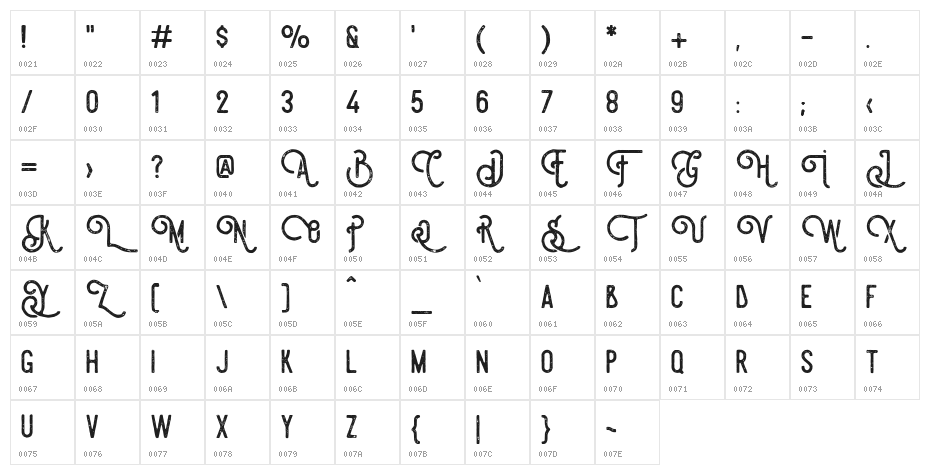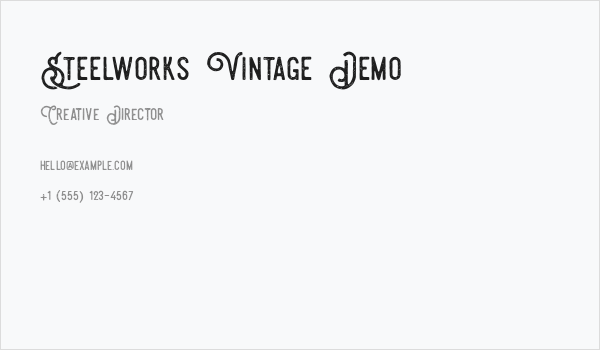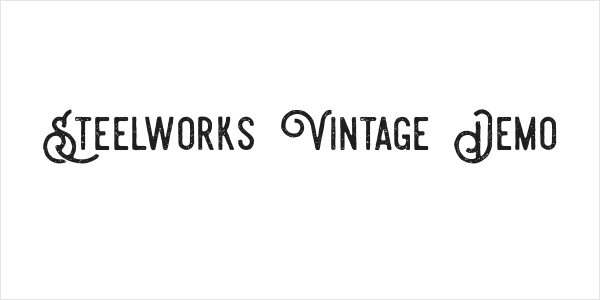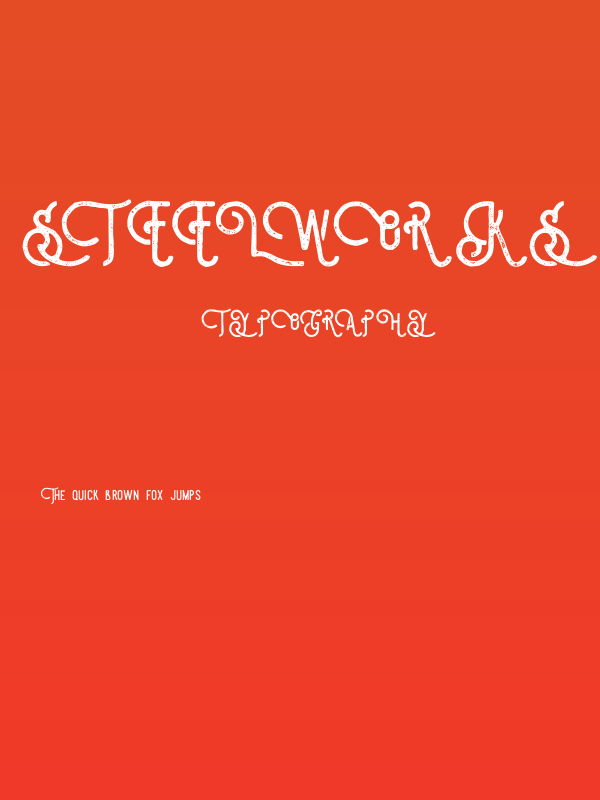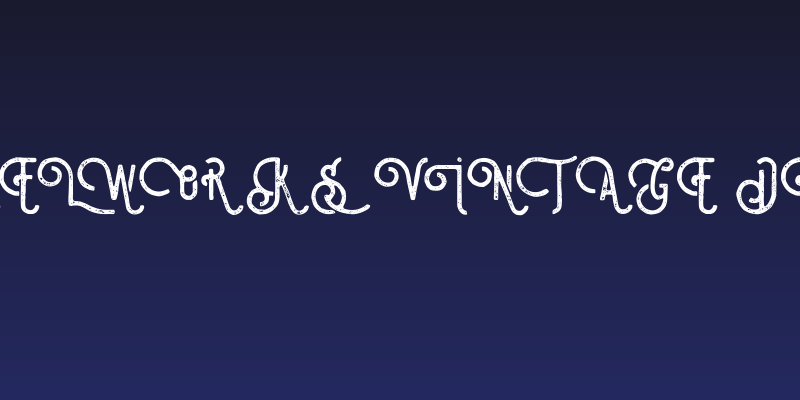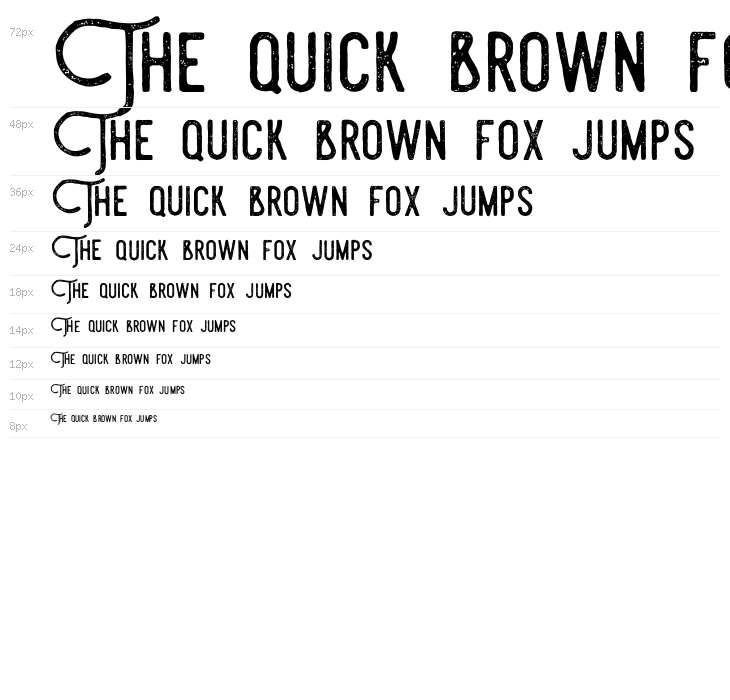
Steelworks Vintage Demo Font
✎ Retro
| Kategorien | Retro |
| Gesamtstil | Vintage |
| Anwendungsfall | Logos, Headlines, Posters |
| Vorgeschlagene Projekte | Ideal for vintage-themed posters, retro branding, industrial design projects, and apparel graphics. |